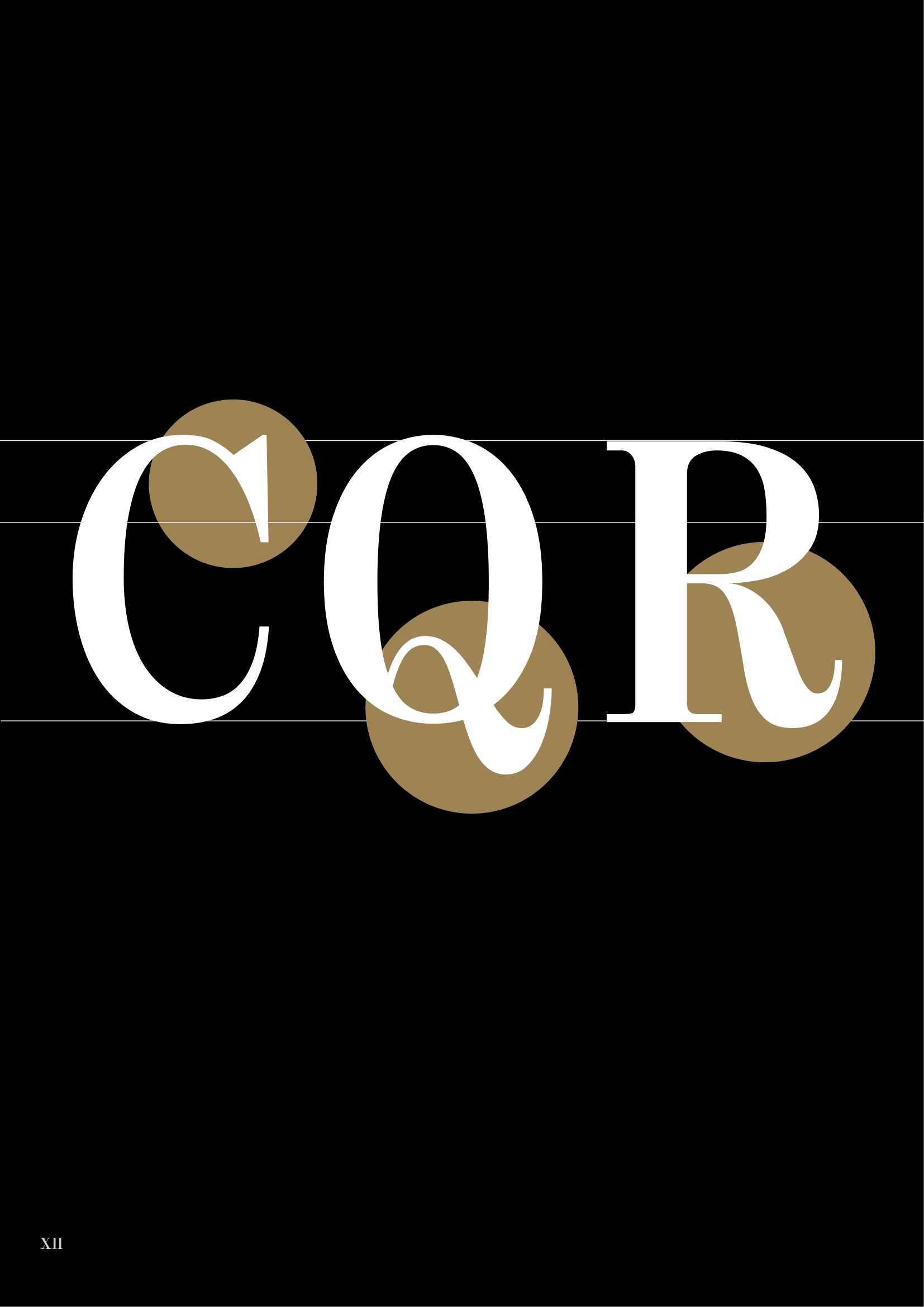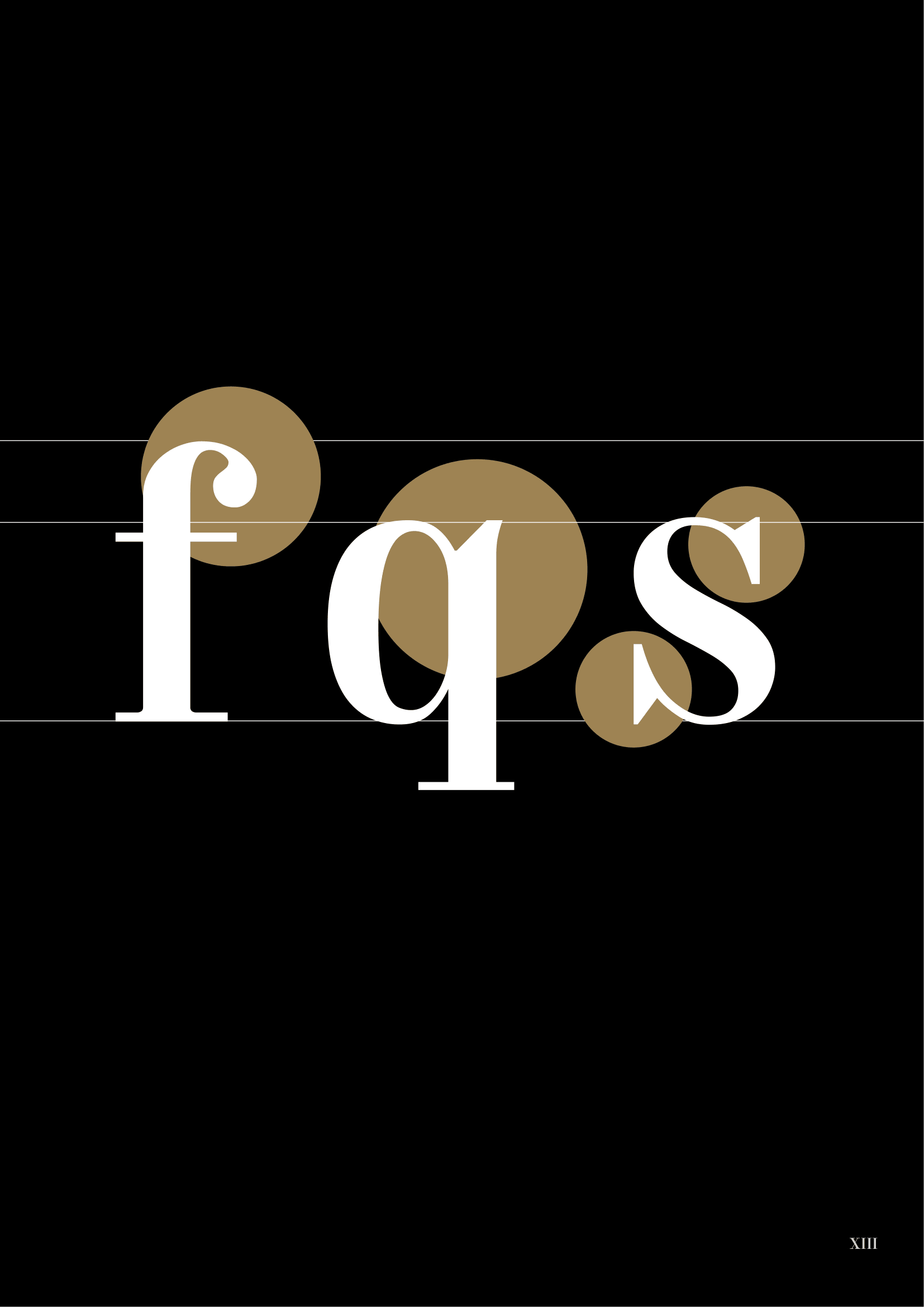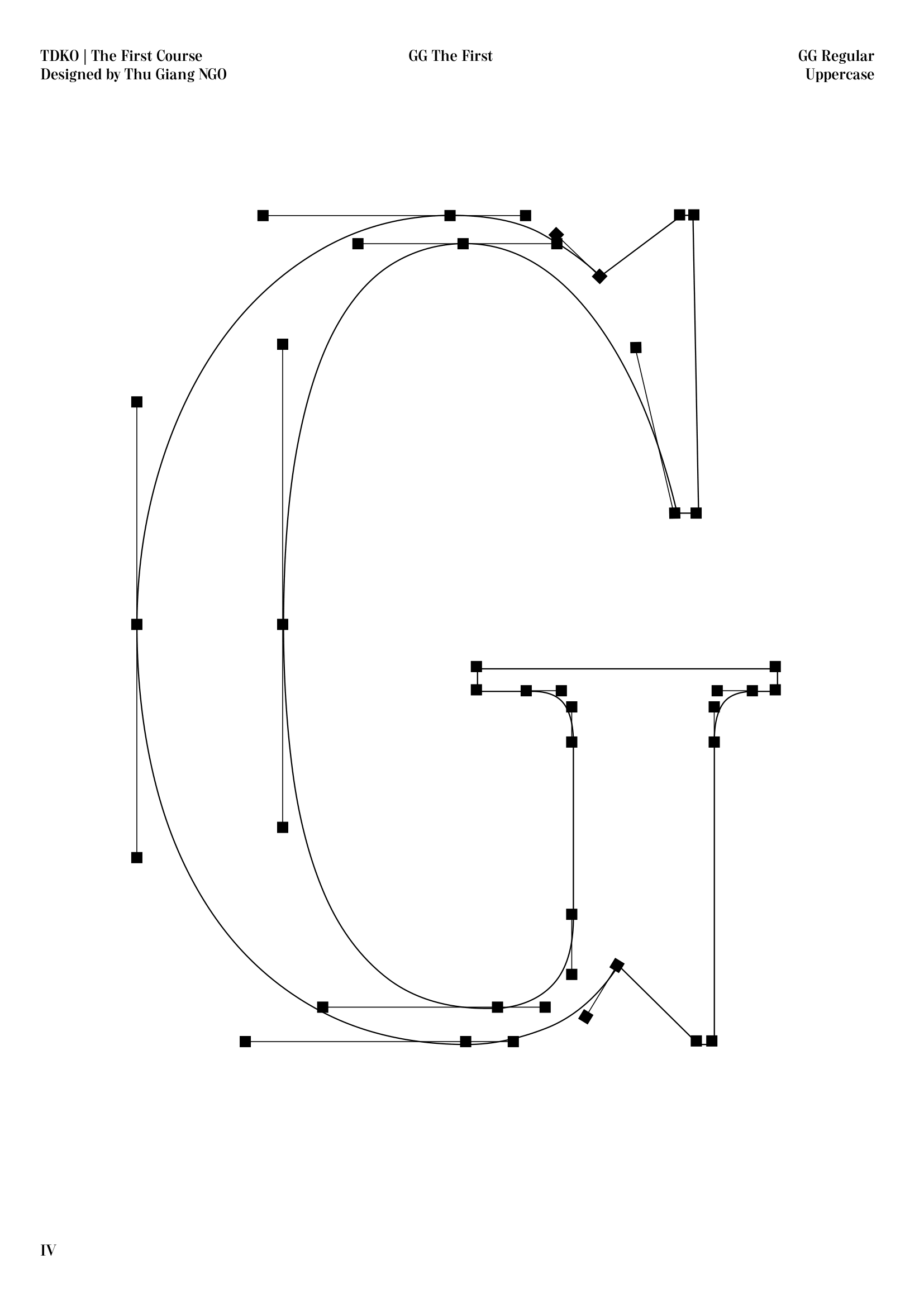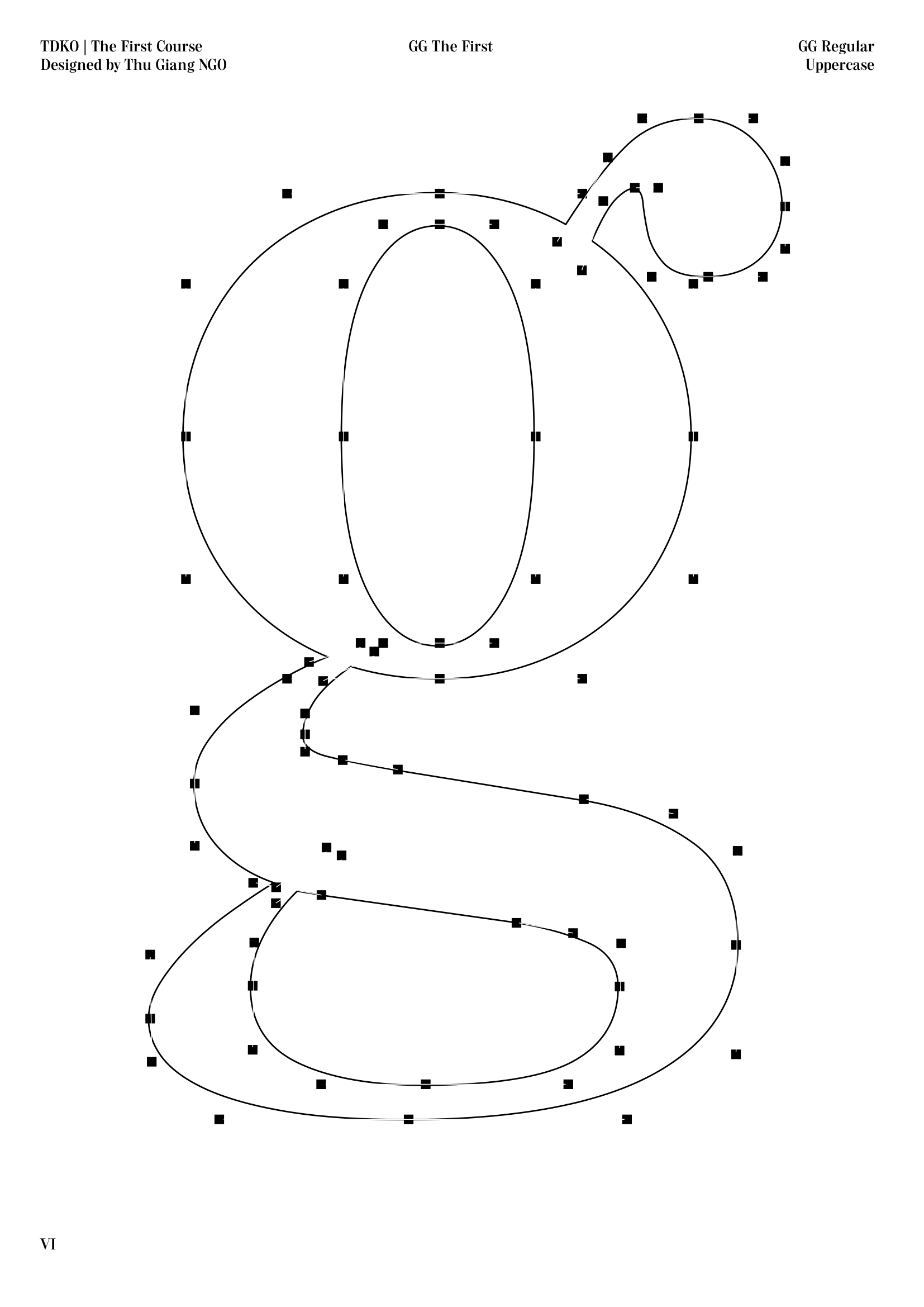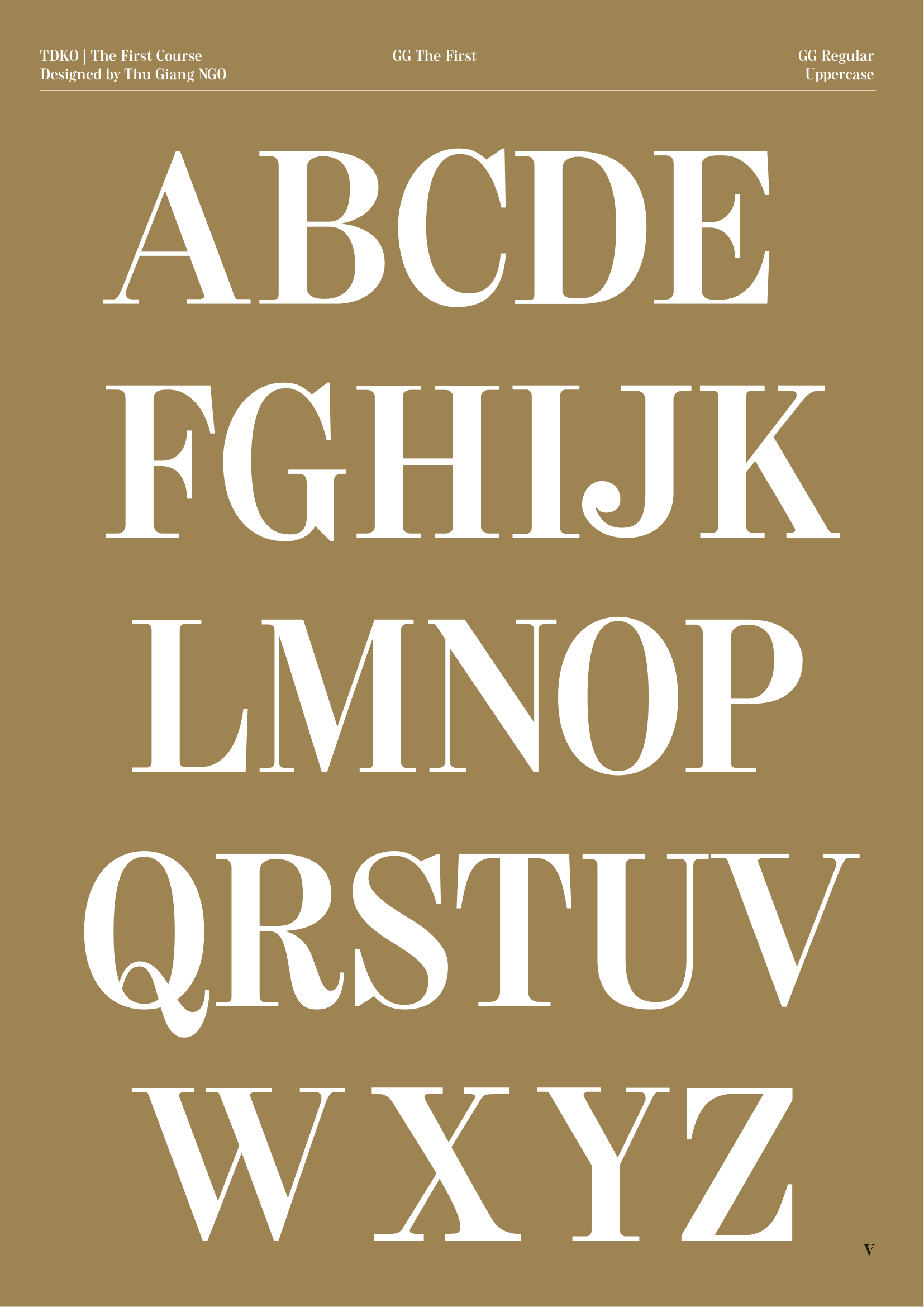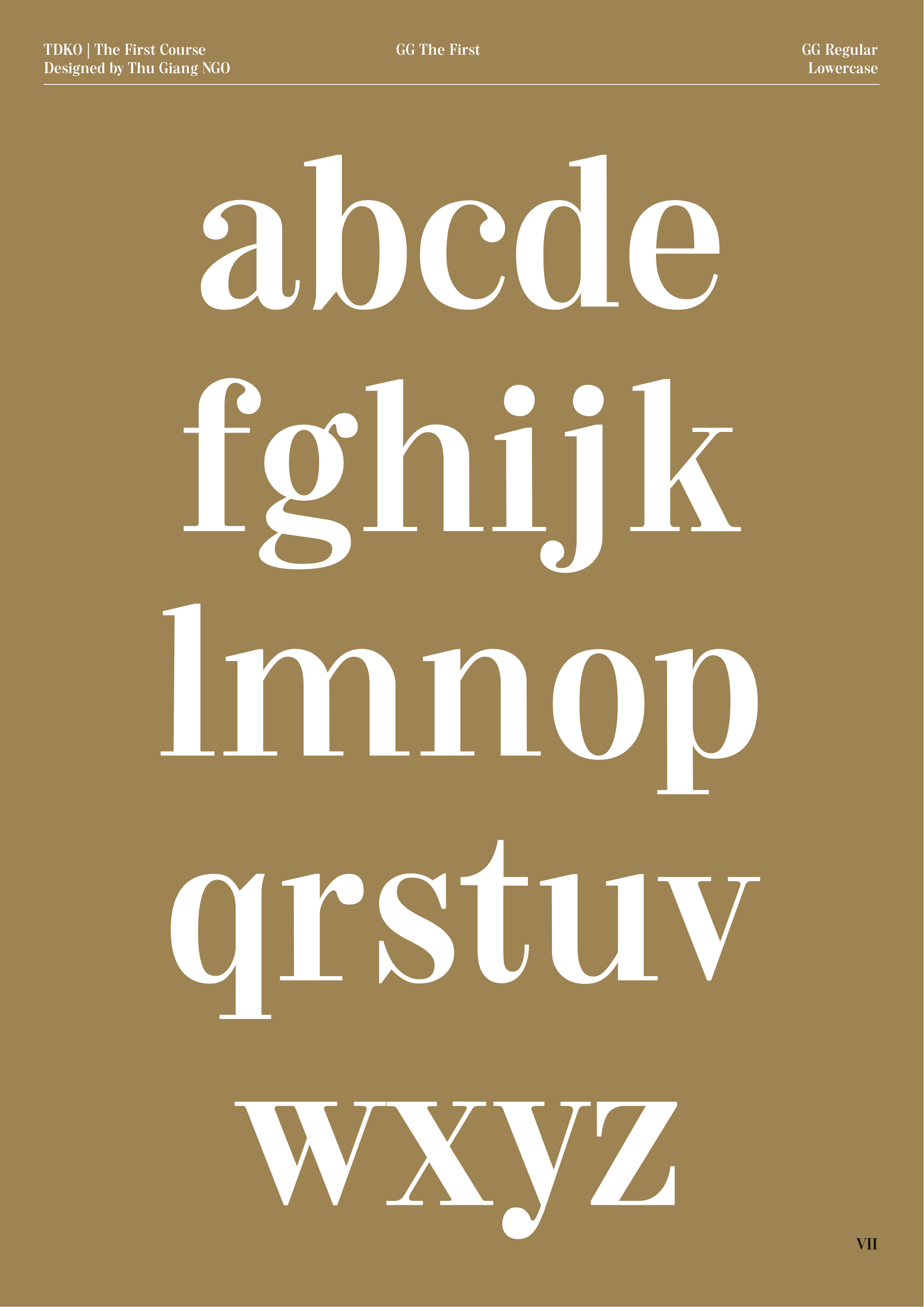
GG The First
Về GG The First: GG The First là phông kiểu modern serif, lấy Ludlow Century của Ludlow Typograph Company làm tiền đề phát triển. Tương phản không quá cao, trục thẳng và tỷ lệ hơi bè tạo nhịp chữ ổn định và một chút điệu đà, phù hợp làm tiêu đề cho các dự án thiên về thời trang.
Modern Serif
Display
Ngô Thu Giang